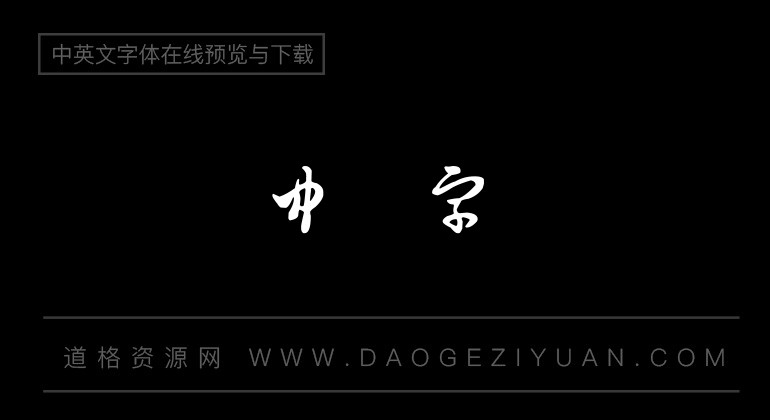
王羲之草书-深林流水书体
王羲之草书-深林流水书体是由中国古代书法家王羲之创作的一种书法体。它以笔画细腻、笔势舒缓、笔锋流畅、笔划清晰、结构紧凑为特点,具有极高的艺术价值和文化价值。它具有淡雅、柔和、流畅、细腻、清晰等特点,是中国书法史上最著名的体式之一。
王羲之草书-深林流水书体是一款非常不错的手写艺术字体,具有很好的视觉感,适合于文化类的宣传设计、商业类品牌的广告和产品包装设计以及个性化文字排版等较多场景。